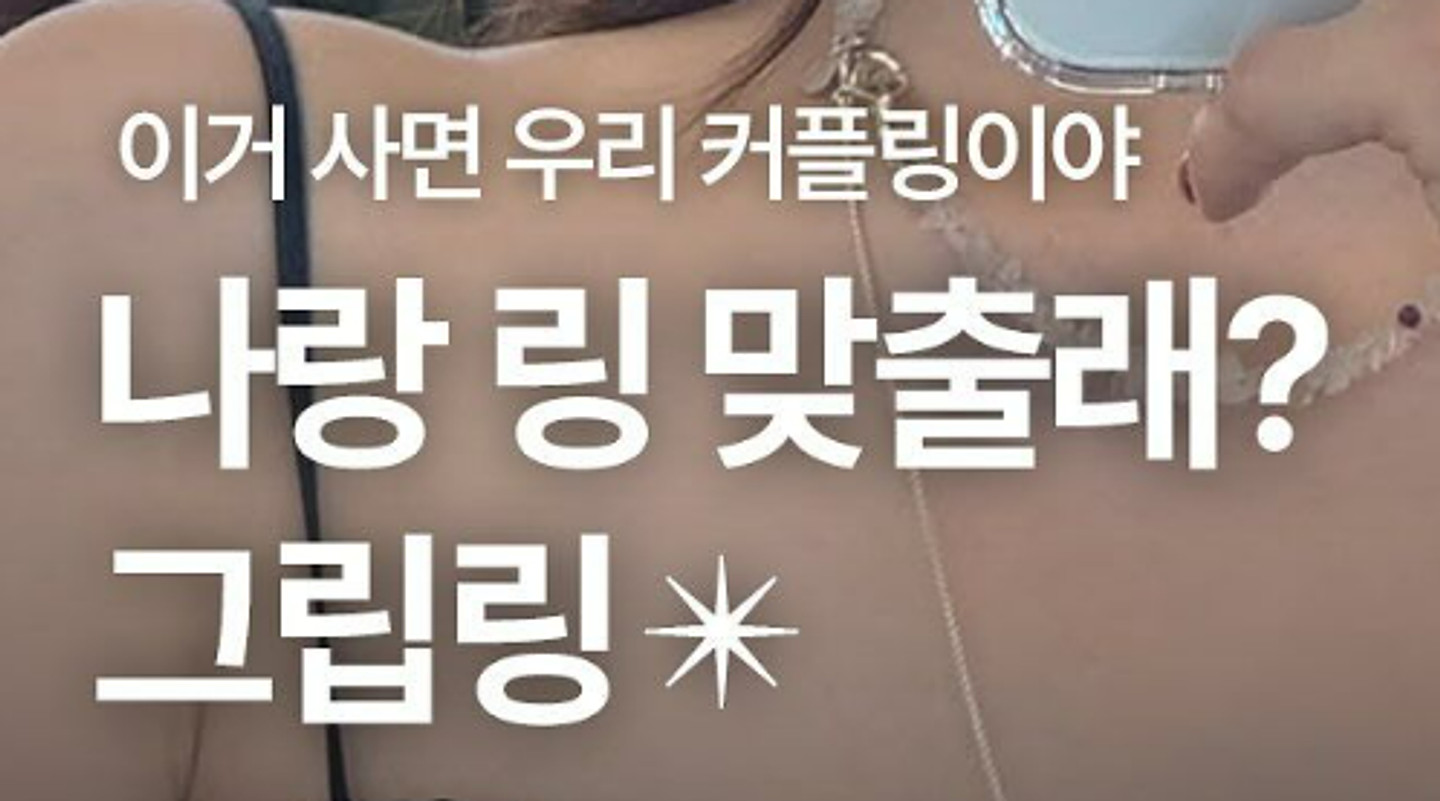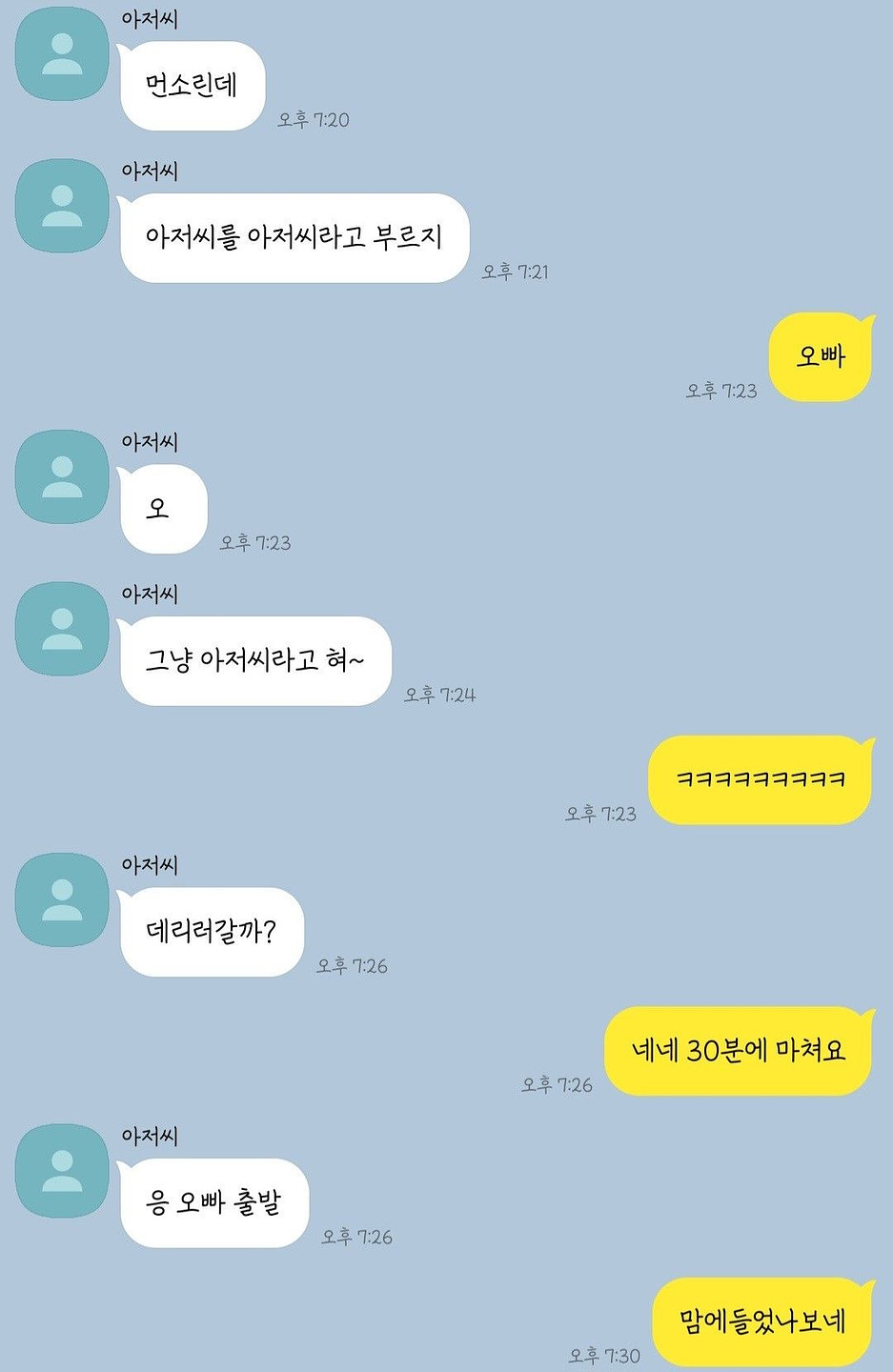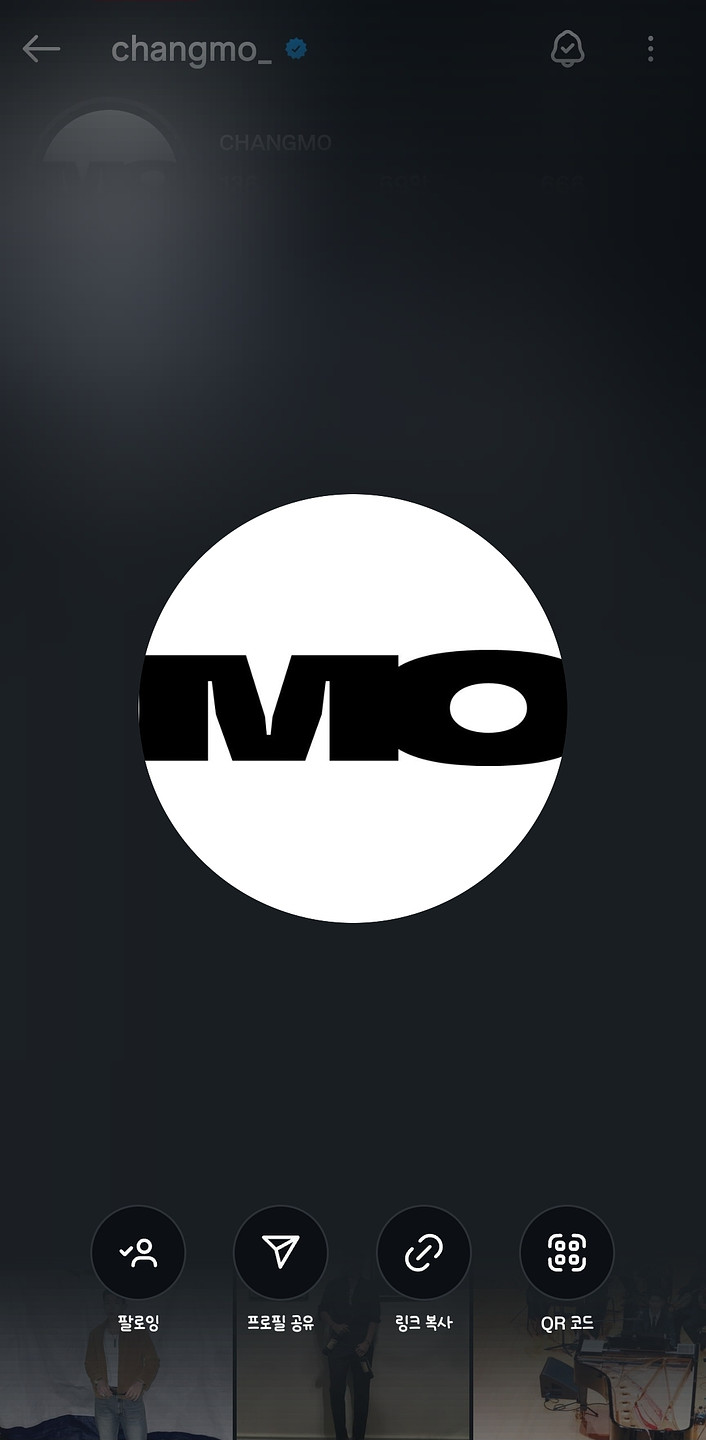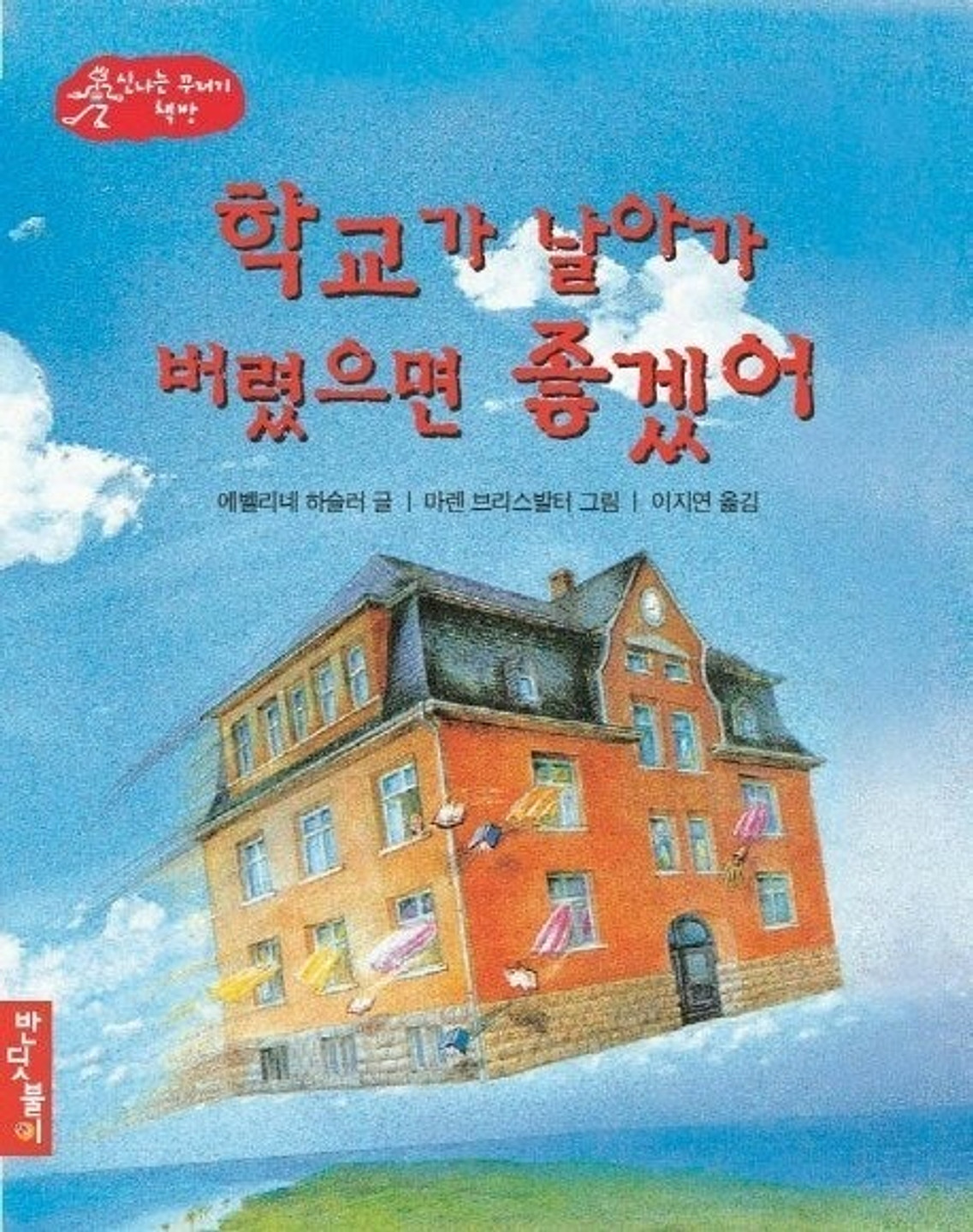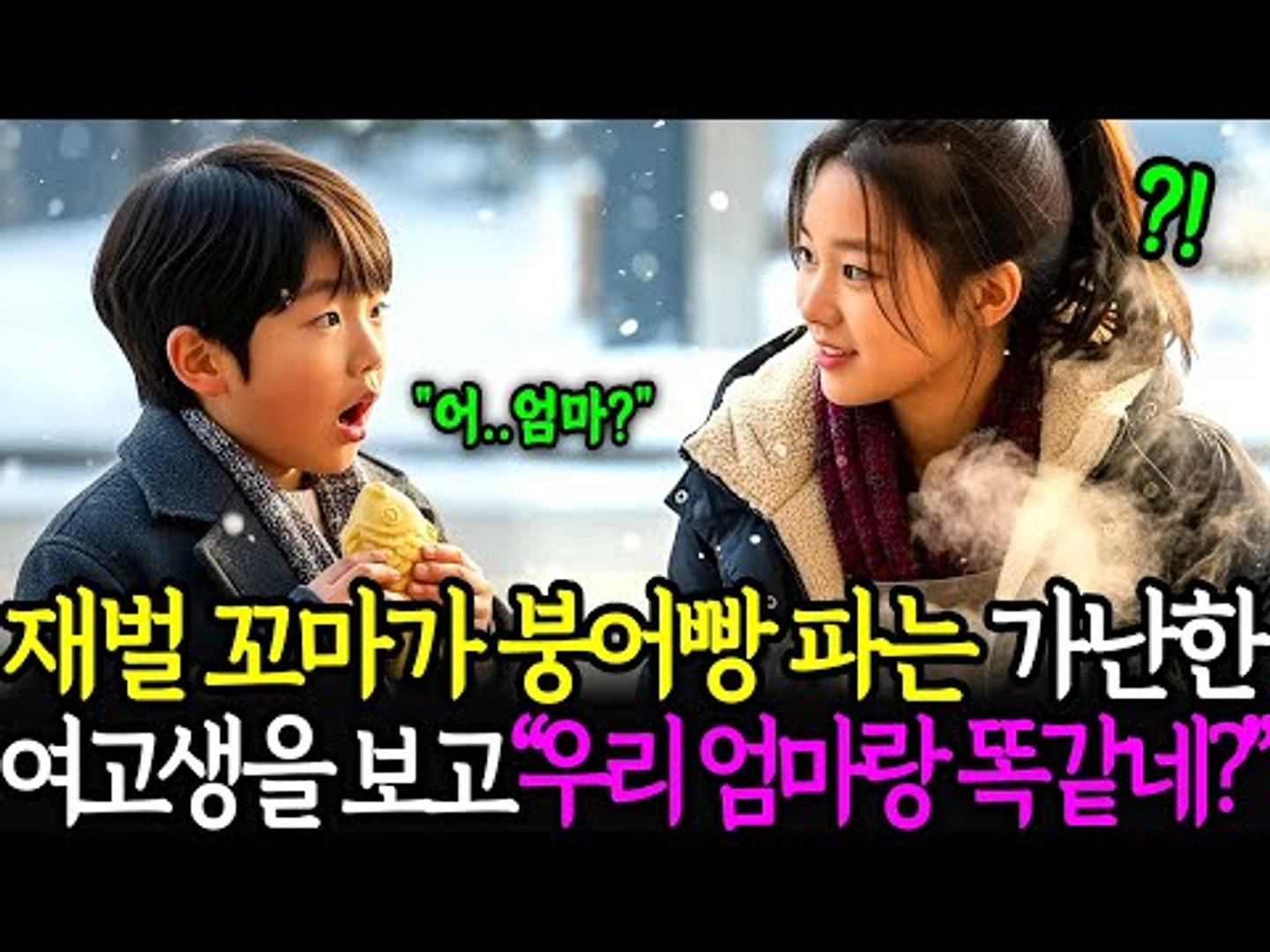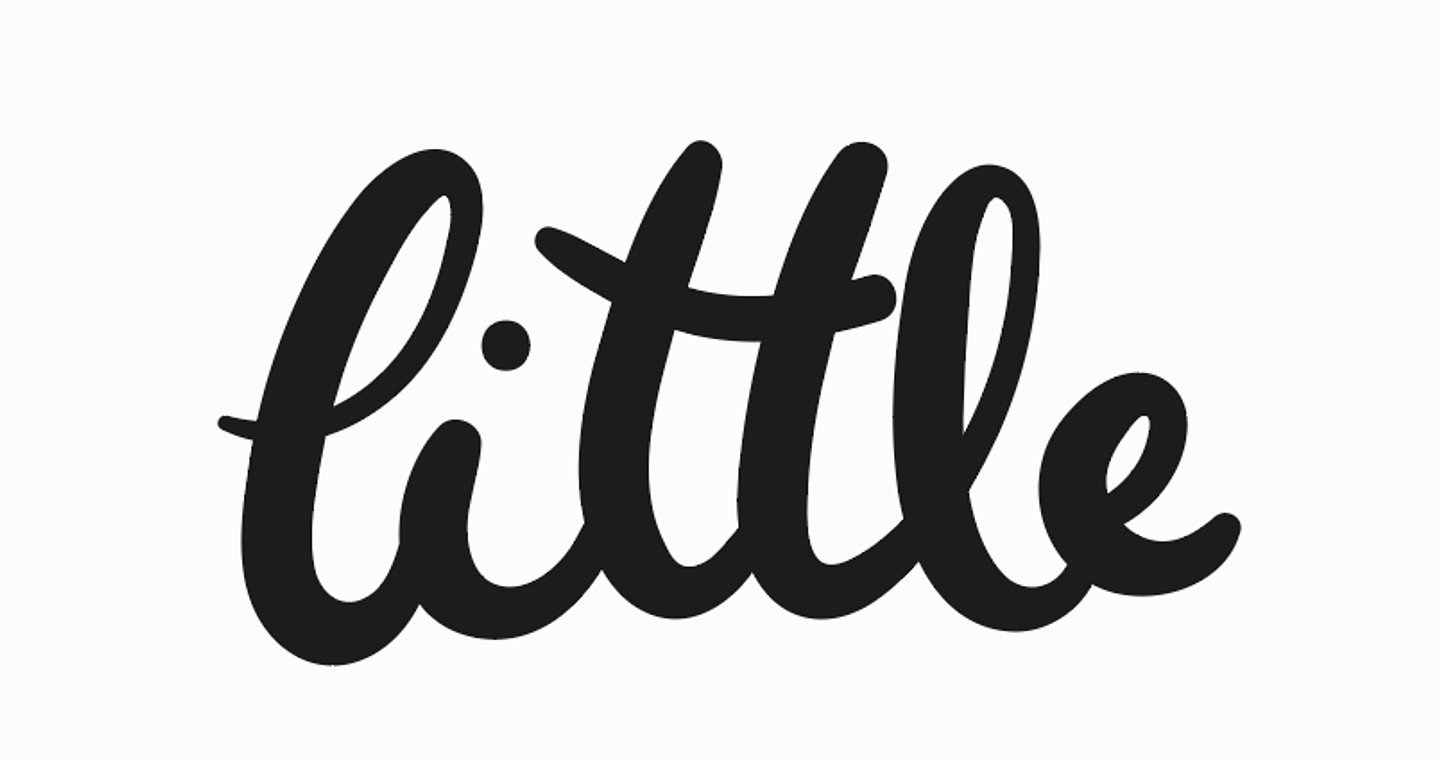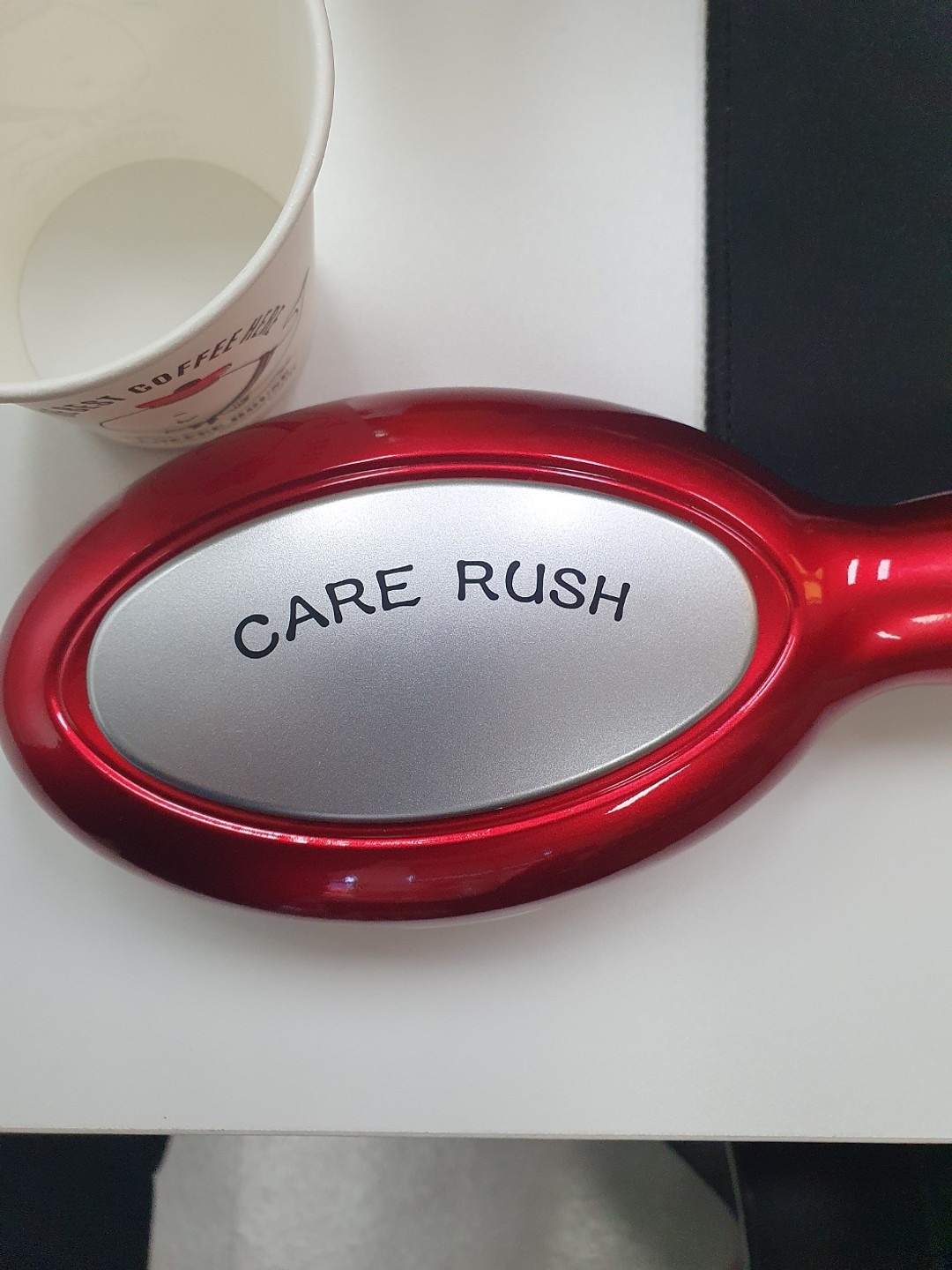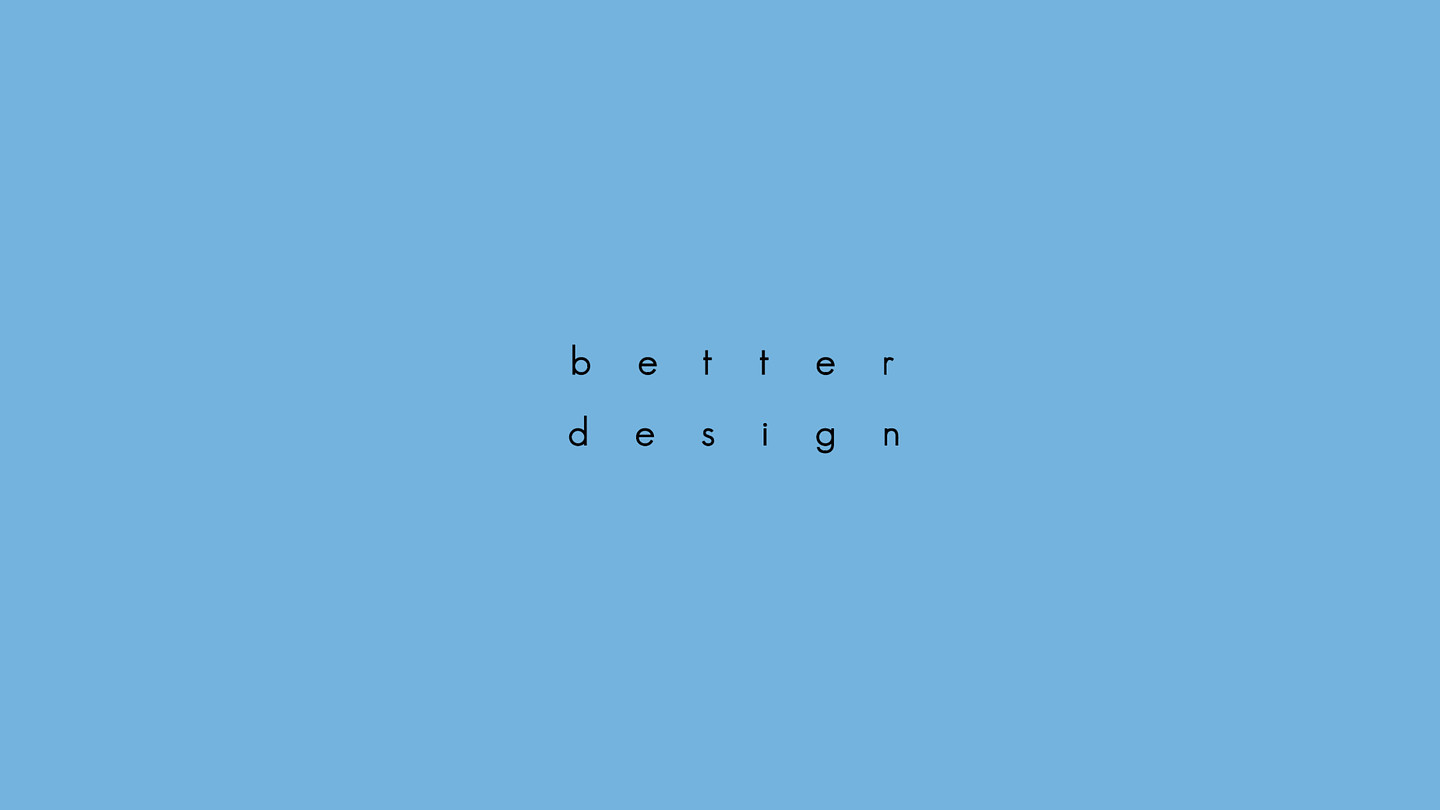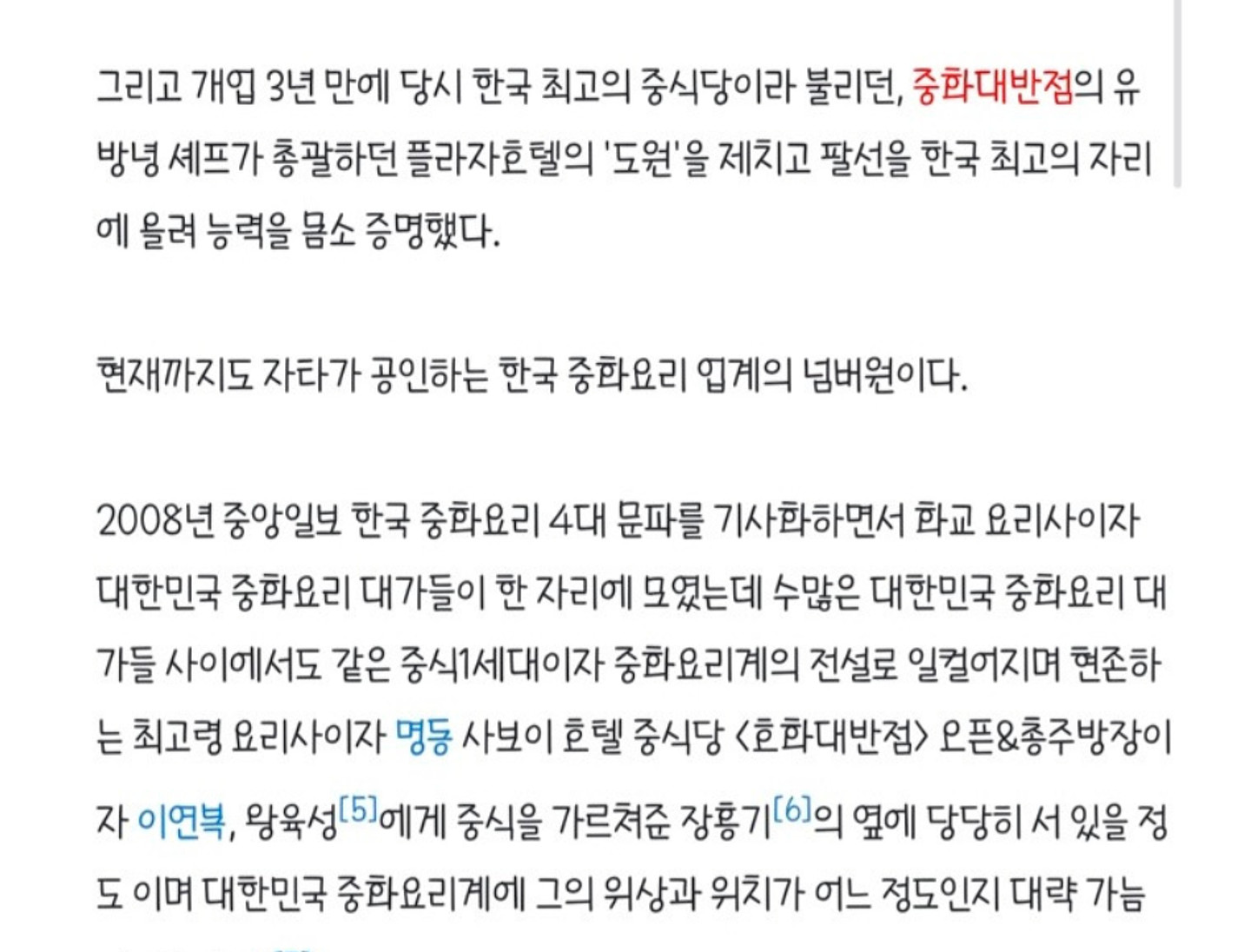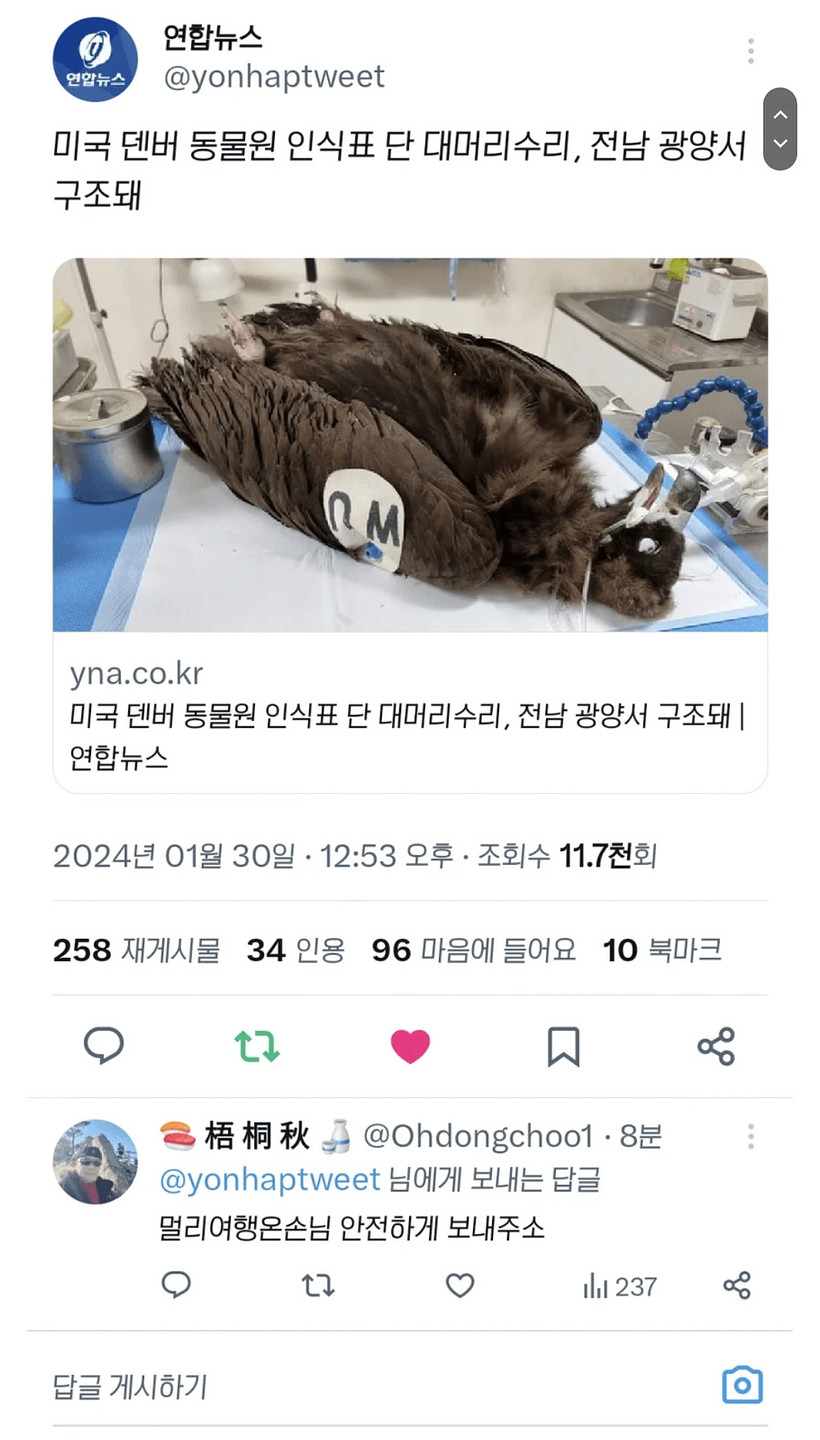
오른쪽이 조금씩 올라가는데,,, 이게 무슨 폰트 어떤건지 찾아주세요...!
무슨 폰튼가요
서교공 로고 폰트 뭔가요... 1984 대화나눔 웅성웅성같은데... 아니에요
SBS로고 폰트 뭘까요?
어디 폰트인가요? 정말 찾고 찾던 폰트인데 인터넷에서 주운 거라 어디꺼인지도 모르겠어요...
이 폰트 아시는 이쁘고 잘생긴 분 ? 출처: 시미즈 유튜브
한국은 처음이지 폰트 어떤거 쓴건가요?
어떤 폰트일까요??
이 폰트 뭘까요?ㅠㅠ 궁금해요!!!!
폰트 이름이 궁금합니다! 감사합니다
무슨 폰트인가열
이거 글씨체 뭘까요?
유튜브 보다가 예전 무료 폰트였던 것 같은데 찾아도 안나오네요ㅠㅠ 뭘까요?
야노시호님 유튜브에 나온 글씨체 뭔 지 알 수 있을까요?????
상단 큰 폰트 정보 궁금합니다.
폰트 정보 알 수 있을까요?
무슨폰트인가요 ㅜㅜㅜ
폰트 궁금해요 비슷한거라도 제발 ㅠㅠ
폰트 궁금해요 ㅜㅜ 미리 감사합니다!!!
에픽 어플 빨간색 동그라미 그려놓은 저!! 영어 폰트 저거 무슨 폰트일까요? 상업용일까요???
캡컷 기본 폰트.. 시스템이라고만 뜨는데 무슨 폰트일까요?ㅠㅠ 상업적 사용 가능한걸까요?
이 영어 폰트 뭔지 아실까요?
이 폰트 궁금해요
제목과 본문 두가지 모두 알려주세요
이거 카톡 폰트 뭔지 아시는분ㅠㅡㅠ 릴스보다가 진짜 너무 궁금해서 미쳐버릴거같아요 (릴스는 mittsommmer 님 입니다!!)
이거 무슨 폰트인가요????
프리랜서 평균수입 문구 글씨체가 뭘까요..??
혹시 이 이미지에 사용된 정확한 폰트명을 알 수 있을까요? 가장 유사한 폰트는 '온글잎 매일옥자체'인 것 같은데, 완전히 일치하지는 않네요. 감사합니다!!
모든 폰트 다 뒤지고 비교해 봐도 죽어도 안 나와서 최종으로 눈누에 질문드립니다....... 시옷의 머리가 거의 없다는 특징이 있어요. 찾으신 분은 진짜 폰트 박사라고 할 수 있습니다!!
폰트이름 부탁드립니당 감사합니다!!
폰트 알려주세요! 감사합니다^^
큰 글씨랑 작은 글씨 폰트 알수있을까요?
궁금합니닷..
이 폰트 알고싶어요~~
궁금해요..,!
폰트가 뭘까요?
무슨폰트일까요..
요즘 릴스에서 많이 보이는데 무슨 폰트일까요?
이거 무슨 글씨체일까요? 알려주세요 🥺
서체 뭘까요...?
이 폰트 너무 궁금합니다~ 고수님들 알려주세요~
다큐멘터리 보다가 발견한 폰트인데, 이 제목 폰트 혹시 아시는 분 계실까요..?
비디오 폰트? 인데 이런거 비슷한거 눈누에도 있을까요??
이거 무슨 폰트인가용? ㅠㅠ
영문으로 이렇게 각지고 정석 고딕 폰트 뭐일까요?!?!?
이 폰트 어떤 폰트인지 아시는 분.. ㅠ.ㅠ!!